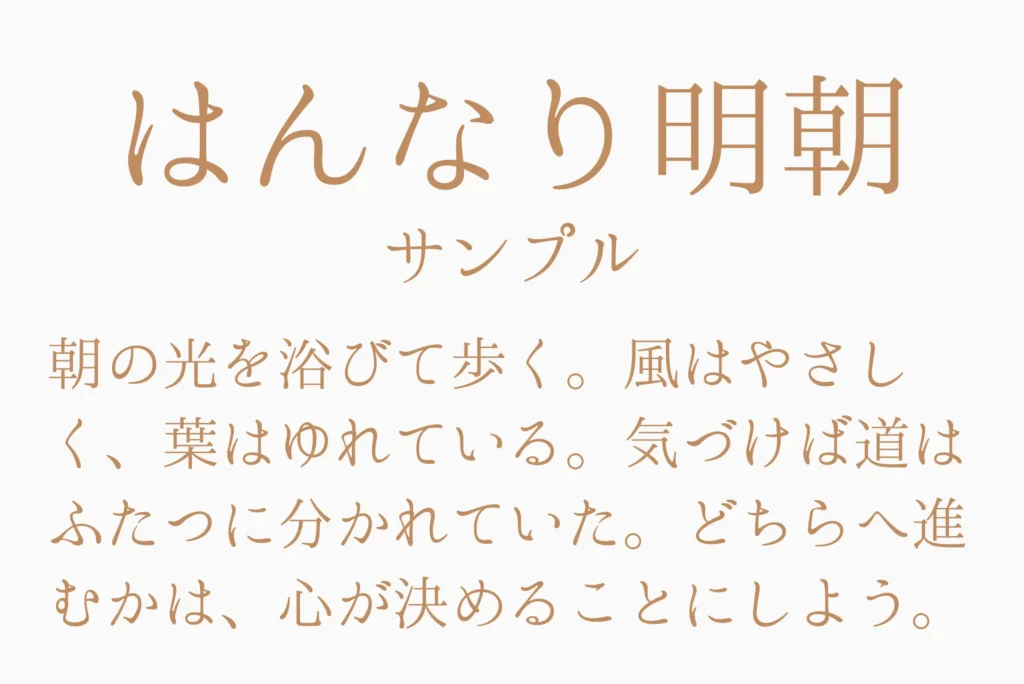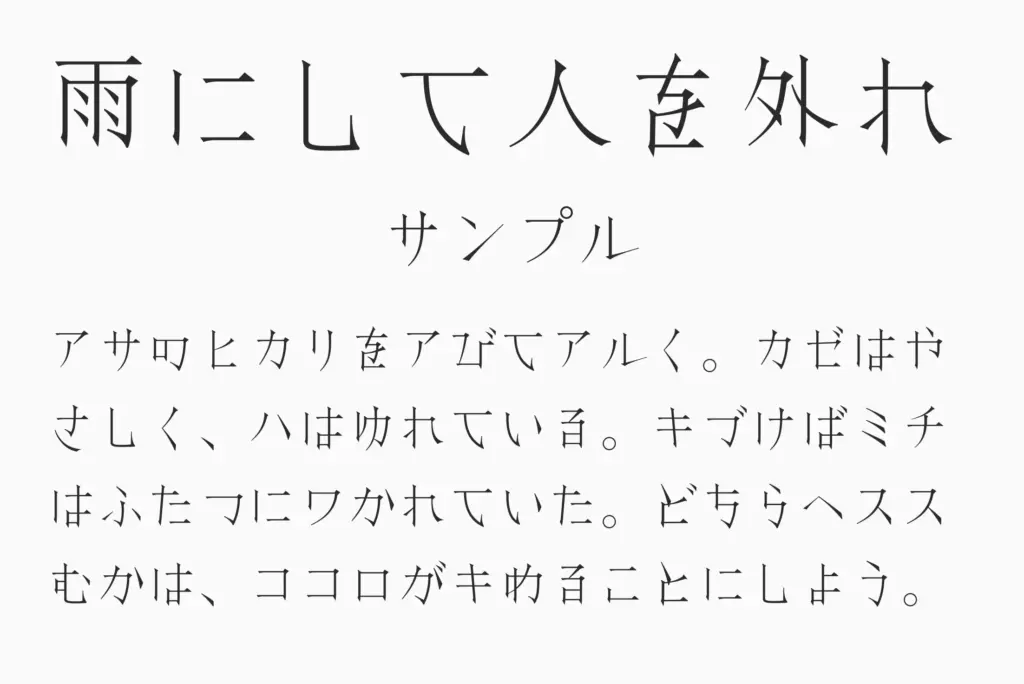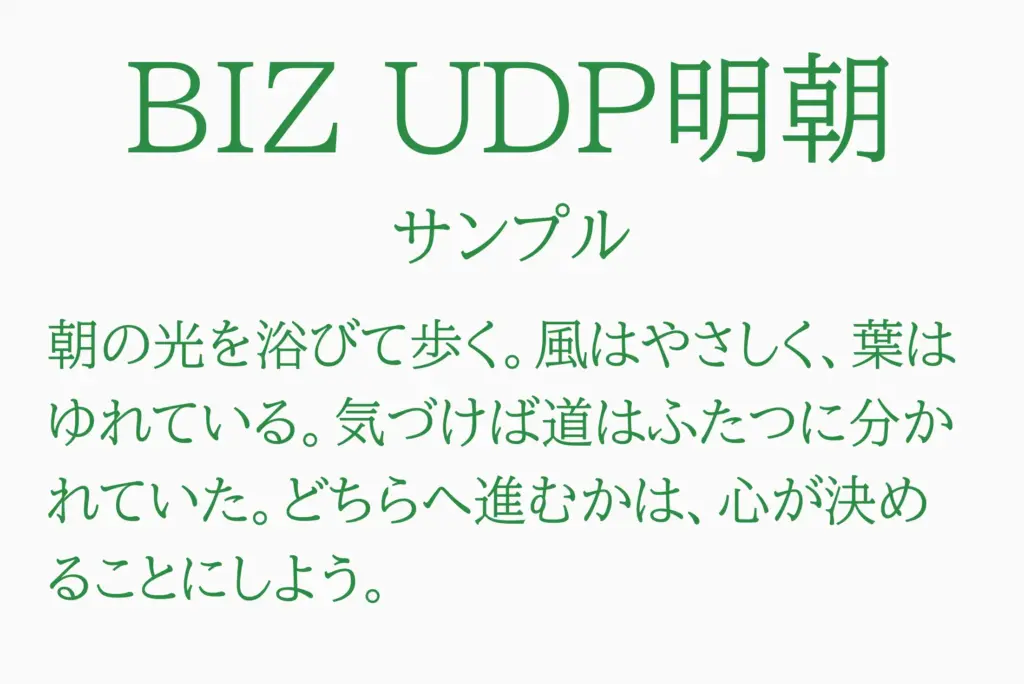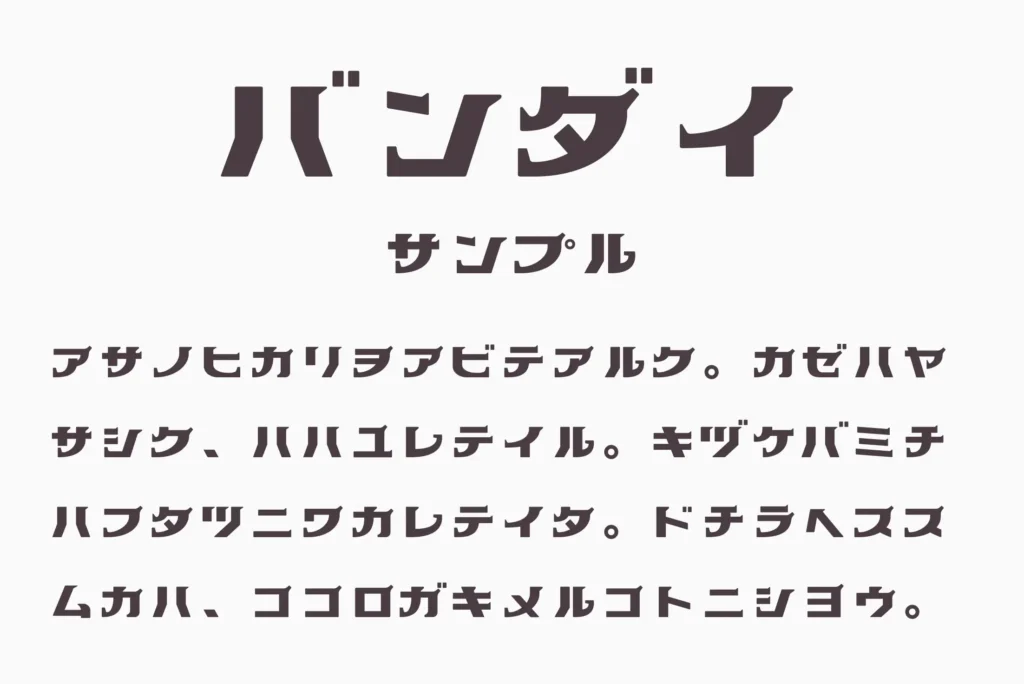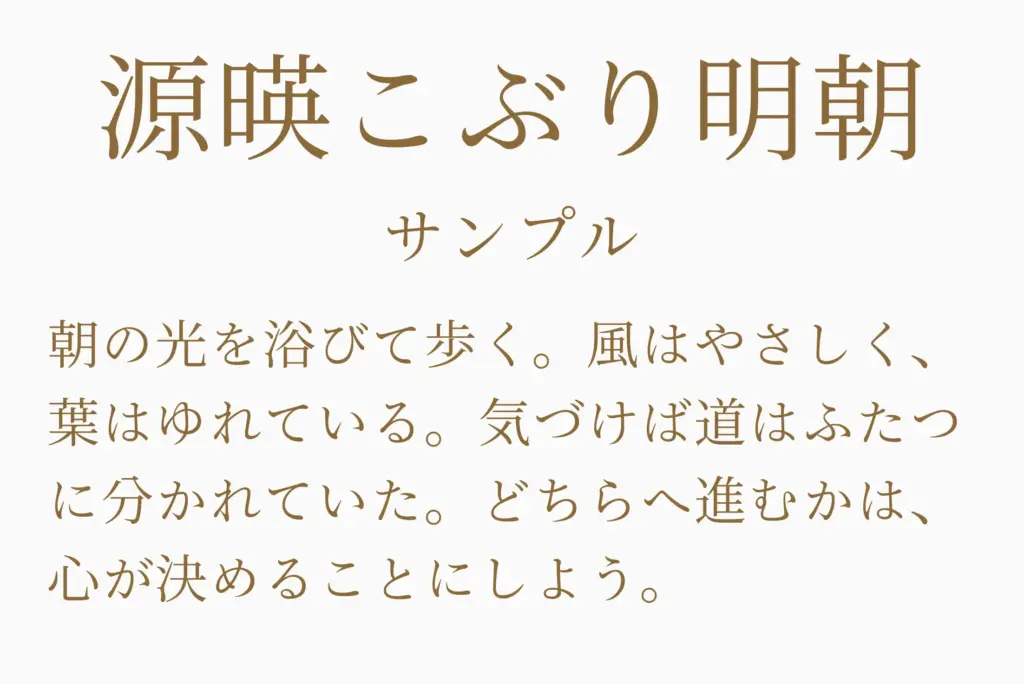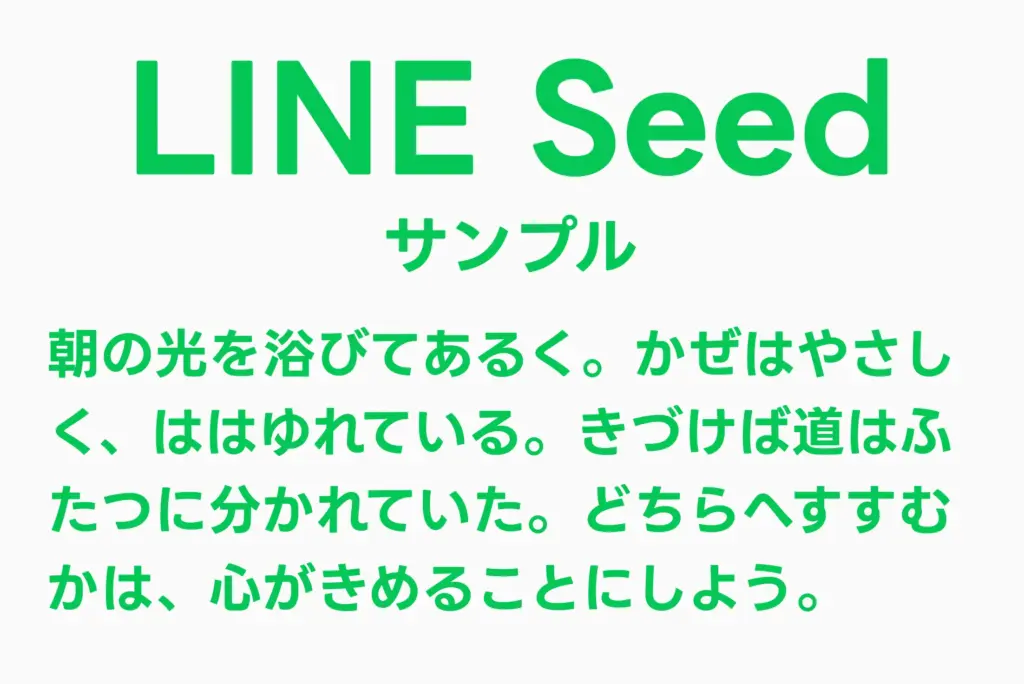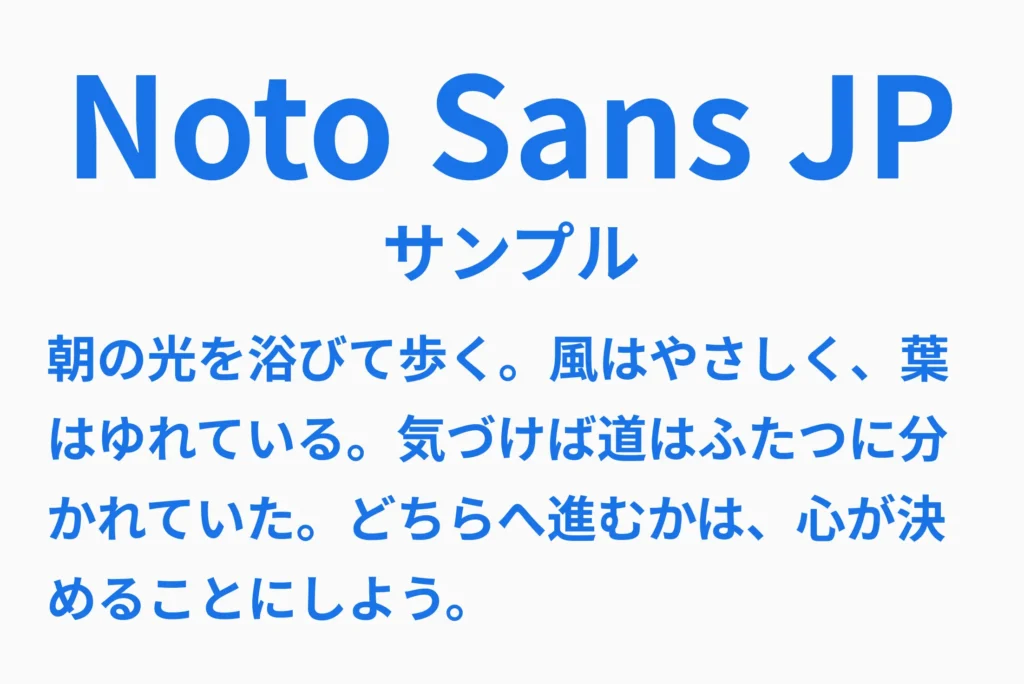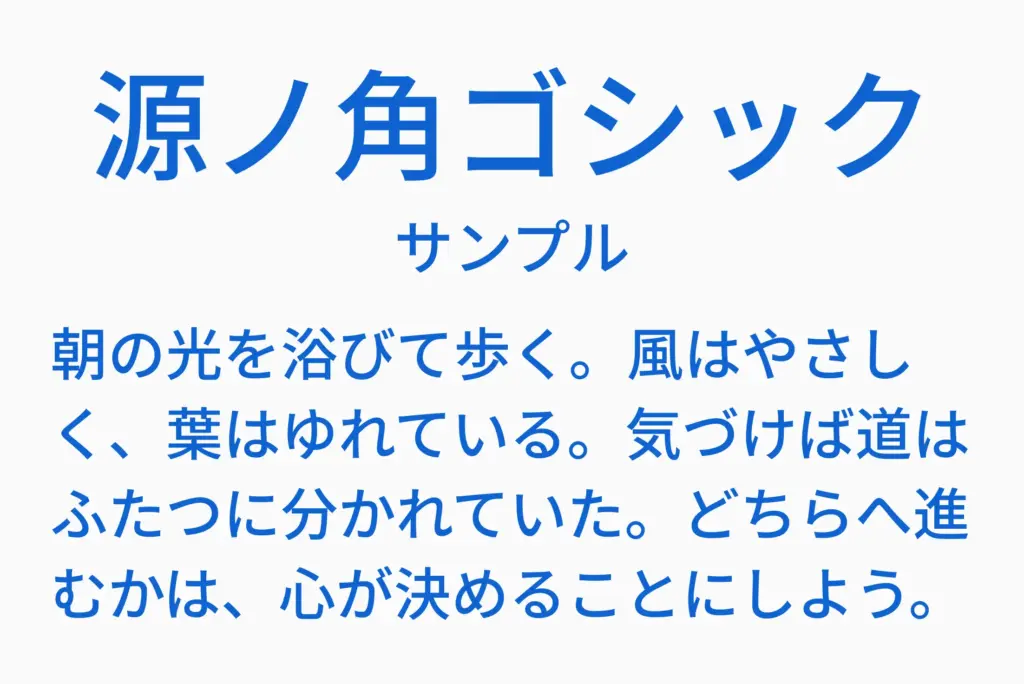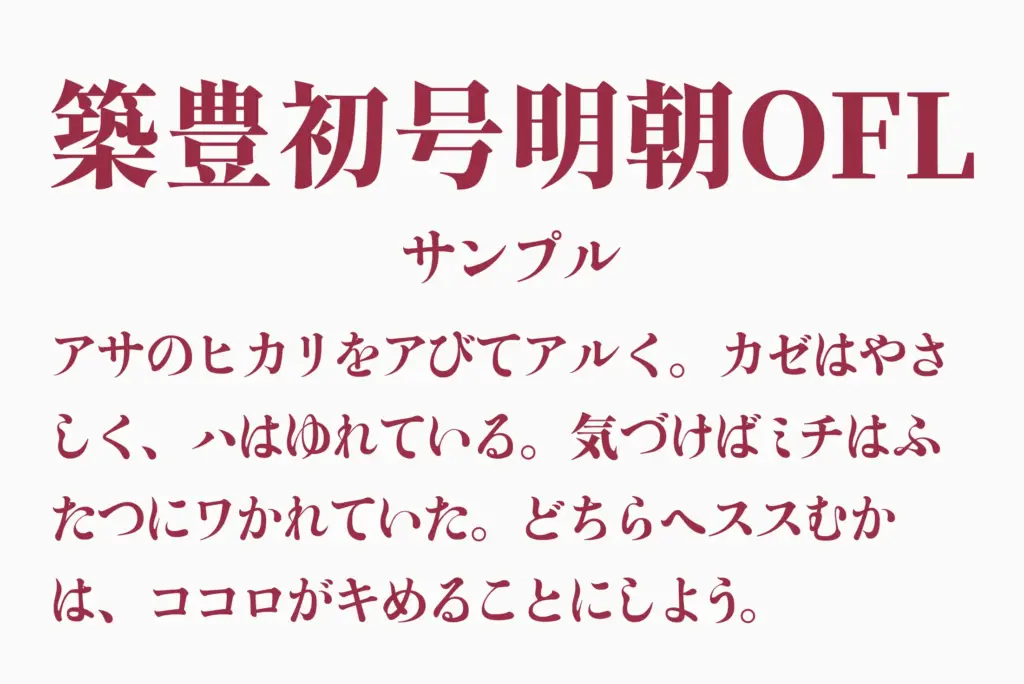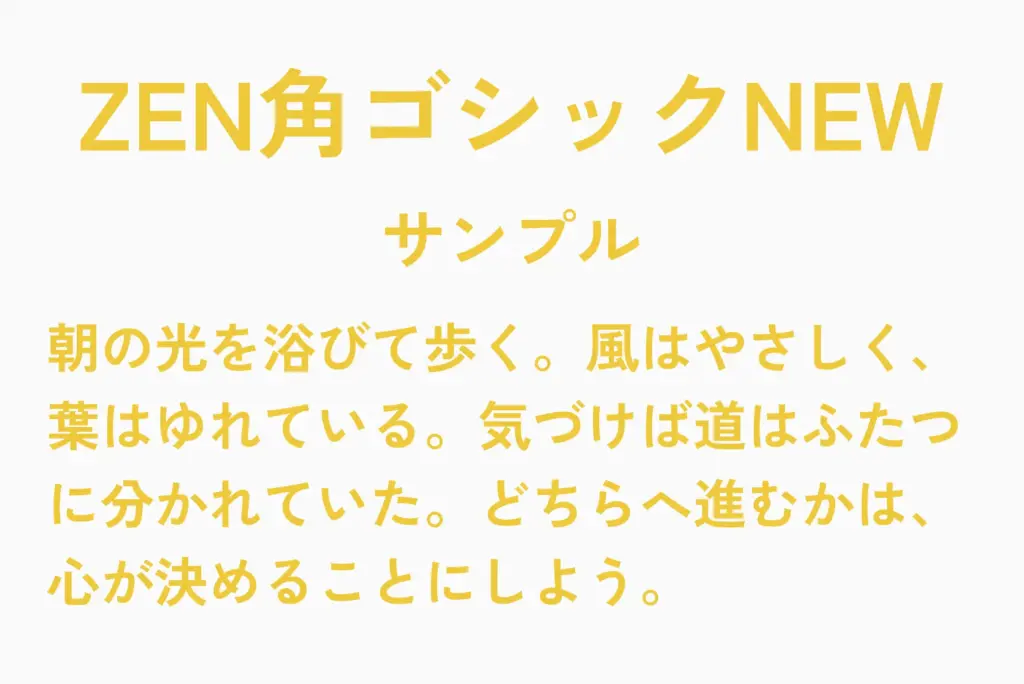
ゴシック体と明朝体の違いとは?特徴・使い分けとおすすめフォント50選【無料・商用OK】
ゴシック体と明朝体の違いとは?特徴・使い分けとおすすめフォント50選
ゴシック体と明朝体の違いとは?
フォント選びで迷ったら、まずは次の3つから選べば間違いありません。
この記事では、ゴシック体と明朝体の違いから、用途別におすすめフォントまでわかりやすく紹介します。
ゴシック体と明朝体の違いとは?特徴・使い分けを初心者向けに解説
フォント選びでよく出てくる「ゴシック体」と「明朝体」。どちらも日本語フォントの定番ですが、見た目だけでなく“読みやすさ・印象・用途”が大きく異なります。
ざっくり言うと、ゴシック体は“読みやすさ重視”のフォント、明朝体は“雰囲気や美しさ重視”のフォントです。
この違いを理解しておくと、Webデザインや資料作成のクオリティが一気に上がります。
ゴシック体の特徴(視認性・均一な線)
ゴシック体は、線の太さが均一でシンプルな構造が特徴のフォントです。
余計な装飾がなく、どんなサイズでも読みやすいため、スマホやPC画面との相性がとても良いです。特にWebサイトやUIなど、「パッと見てすぐ理解できること」が重要な場面で活躍します。
また、カジュアルで親しみやすい印象を与えるため、幅広いジャンルで使いやすいのもポイントです。
明朝体の特徴(ウロコ・強弱のある線)
明朝体は、線に強弱があり、先端に「ウロコ」と呼ばれる三角形の装飾が付いているのが特徴です。
この強弱によって文字にリズムが生まれ、長文でも読みやすく、上品で落ち着いた印象を与えます。書籍や記事、ブランド系のデザインでよく使われる理由もここにあります。
一方で、小さいサイズや画面表示ではやや見づらくなることもあるため、使いどころには少し注意が必要です。
ゴシック体と明朝体の違いを比較【一覧表】
ゴシック体と明朝体の違いは、文章だけでは分かりにくいこともあります。
そこで、特徴や用途を一覧で比較できるようにまとめました。
比較項目ゴシック体明朝体
見た目の特徴線の太さが均一で、すっきり見やすい線に強弱があり、ウロコが付いた上品な印象
視認性高いやや高い
可読性高い高い
向いている用途Web、UI、資料、バナー、プレゼン記事、LP、書籍、ブランド、見出し
向いている印象シンプル、親しみやすい、現代的上品、高級感、落ち着き、世界観
初心者向け度★★★★★★★★★☆
シーン別の使い分け(ビジネス・デザイン・Web)
フォントは「なんとなく」で選ぶより、シーンに合わせて使い分けるのが超大事。
ビジネス資料・プレゼン
ゴシック体がおすすめ
視認性が高く、情報が伝わりやすいのでミスがない
Webサイト・UI
基本はゴシック体
スマホでも読みやすく、ユーザー体験が良くなる
記事・ブログ・長文コンテンツ
明朝体も◎
読みやすさ+落ち着いた印象で没入感が出る
ブランド・高級感を出したいデザイン
明朝体が最適
一気に「ちゃんとしてる感」「世界観」が出る
ゴシック体フォントおすすめ一覧|無料・商用OK含む
スタンダードゴシック(万能・読みやすい)
Noto Sans JP
すっきりとした直線的な骨格と、整った余白バランスが特徴のゴシック体フォントです。クセが少なく非常に読みやすいため、長文でもストレスなく視認できます。ビジネス資料やWebサイト、UIデザインまで幅広く対応できる万能フォントです。
源ノ角ゴシック
AdobeとGoogleが共同開発した、スタンダードなゴシック体フォントです。安定した文字設計で読みやすく、本文から見出しまで幅広く使いやすいのが魅力です。Web・印刷・資料など、さまざまな場面で活躍します。
LINE Seed
LINE公式が提供する、高い視認性を持つゴシック体フォントです。文字の可読性を重視して設計されており、小さなサイズでも崩れにくいのが特徴です。UIやアプリ、Webサービスなど実用性重視のデザインに向いています。
さわらびゴシック
シンプルで親しみやすいデザインが特徴のゴシック体フォントです。やや丸みのある柔らかな線で構成されており、堅すぎない印象に仕上がります。ブログやWebサイト、ナチュラル系のデザインに使いやすいフォントです。
丸ゴシック(やさしい・親しみやすい)
Rounded M+
Rounded M+サンプル
丸みのあるやさしいフォルムが特徴のゴシック体フォントです。整った字形で可読性が高く、親しみやすさと使いやすさを両立しています。子ども向け・女性向け・SNSデザインなどに取り入れやすいフォントです。
小杉丸
丸みのある安定したフォルムが特徴のゴシック体フォントです。視認性とやさしさのバランスがよく、文字数が多い場面でも自然に読みやすく仕上がります。Webや資料、UIなど幅広い用途で使いやすい丸ゴシックです。
はこべら丸ゴシックB
しっかりとした太さと丸みを兼ね備えたゴシック体フォントです。やさしい印象を持ちながらも存在感があり、見出しにも使いやすいのが魅力です。女性向けやポップなデザインによく合います。
ふんわりラウンド
名前の通り、柔らかく軽やかな印象を持つ丸ゴシックフォントです。全体にやさしい雰囲気があり、親しみやすいデザインを作りたいときに向いています。ナチュラル系やカジュアルなデザインにおすすめです。
こども丸ゴシック
子ども向けにもなじみやすい、やさしく可愛らしい印象のフォントです。丸みの強い字形で、堅さを抑えながらも読みやすさを保っています。教育系やキッズ向けのデザインにぴったりです。
やさしさゴシック
やさしく丸みのあるフォルムが特徴のゴシック体フォントです。読みやすさを保ちながらも、柔らかく親しみやすい印象を与えられます。女性向けデザインやナチュラル系のWebサイトにぴったりのフォントです。
角ゴシック(シャープ・クール)
ZEN 角ゴシックNEW
シンプルでクセのない設計が特徴のゴシック体フォントです。現代的なバランスで整えられており、読みやすさとデザイン性を両立しています。Web・UI・資料など幅広い用途に対応できる万能フォントです。
源暎きわみゴ
力強さと可読性を兼ね備えたゴシック体フォントです。太めの線でしっかりとした印象を与え、見出しやタイトルにも存在感を出せます。視認性が高く、インパクトを出したい場面に向いています。
かんじゅくゴシック
やや柔らかさを残しつつも、安定感のあるゴシック体フォントです。親しみやすさと視認性のバランスがよく、堅すぎないデザインにもなじみます。カジュアルな見出しやWebデザインにも使いやすいフォントです。
押出Mゴシック
立体感を感じさせるデザインが特徴のゴシック体フォントです。視線を引きつける力があり、短い言葉でもしっかり印象を残せます。タイトルやロゴなど、存在感を出したい場面に向いています。
JKゴシックM
迷った場合は、Noto Sans JPなどの定番フォントから使い始めるのがおすすめです。
フォント選びに迷った場合は、まずは定番フォントから使い始めるのがおすすめです。
そこから用途に応じてフォントを変えていくことで、デザインの完成度が安定します。
迷ったらこの3つから選べばOK
• 迷ったら → Noto Sans JP
• おしゃれ重視 → Zen Old Mincho
• やさしい印象 → Rounded M+
用途が決まっていない場合は、まず定番フォントから使い始めると失敗しにくいです。
まとめ|ゴシックと明朝を使い分けるだけでデザインは変わる
フォントは「なんとなく」で選ぶより、用途に合わせて使い分けることで、デザインの完成度が大きく変わります。
• 読みやすさ重視 → ゴシック体
• 雰囲気・高級感 → 明朝体
• やさしさ・親しみ → 丸ゴシック
迷った場合は以下の3つから選べば失敗しません。
• Noto Sans JP
• Zen Old Mincho
• Rounded M+
そこから用途に応じてフォントを使い分けることで、より魅力的なデザインに仕上げることができます。